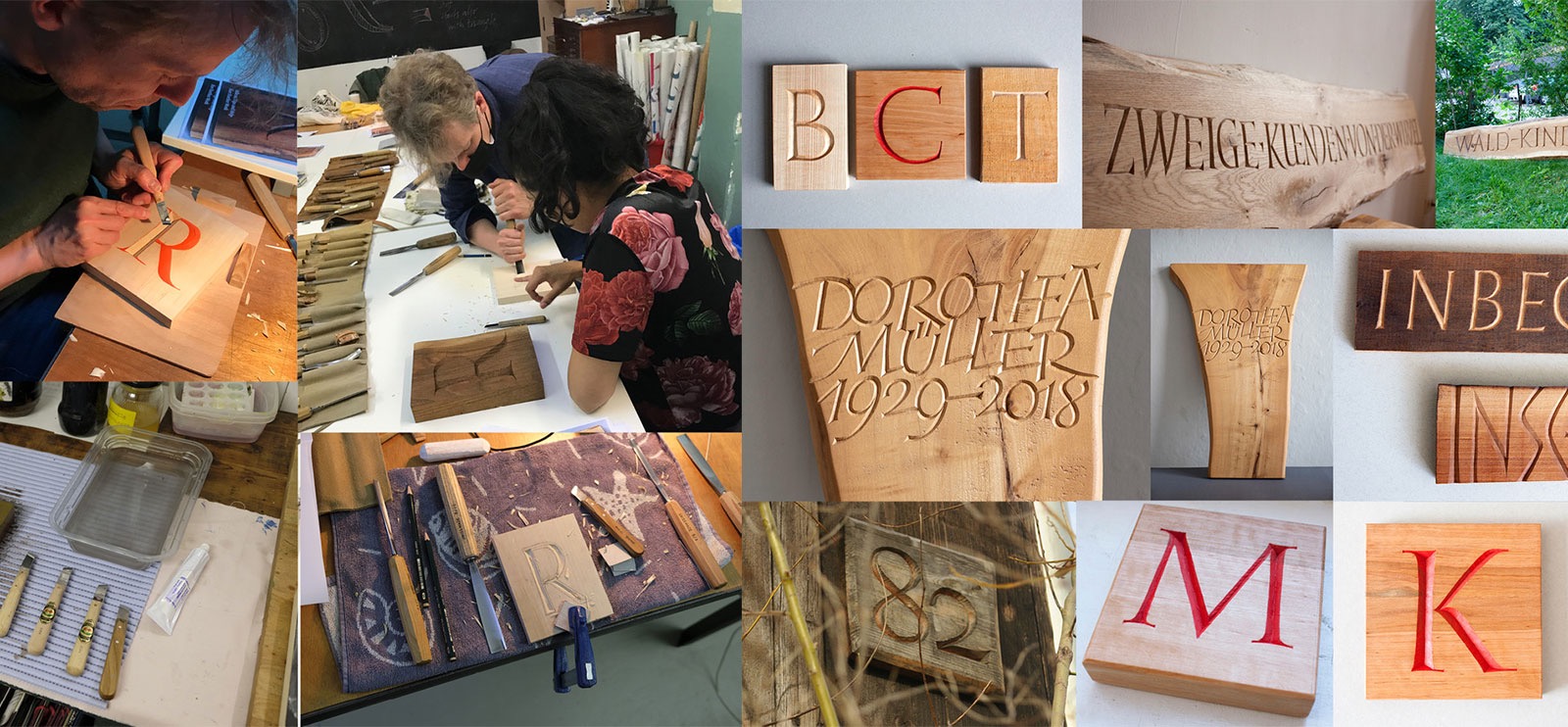
Ein Wochenend-Workshop in der Pavillon-Presse Weimar mit Workshop-Leiter Tobias-David Albert.
Anders als bei Typografie ist ein in Stein oder Holz geschnittener Buchstabe ein dreidimensionales Objekt, bei dem sich Licht und Schatten lebendig erleben lassen. Die klassische Technik von Buchstaben in Holz oder Stein zu schneiden ist ein V-Schnitt. Die Besonderheit von Holz im Vergleich zu Stein ist seine sehr warme Erscheinung. Außerdem läßt das Material überall finden. Es verlangt aber im Gegensatz zum Stein besondere Aufmerksamkeit, da vor allem mit der Maserung gearbeitet werden sollte.
Die Capitalis lässt sich wunderschön mit dem Holzschnitt verbinden aber auch alle andern Schriftformen wie Textura, Fraktur, Unziale oder Serifenlose etc. Zunächst werden Formen geschrieben oder gezeichnet. Dann beginnt die Arbeit mit leicht zu bearbeitenden Laubhölzern wie Birke, Ahorn oder Buche …